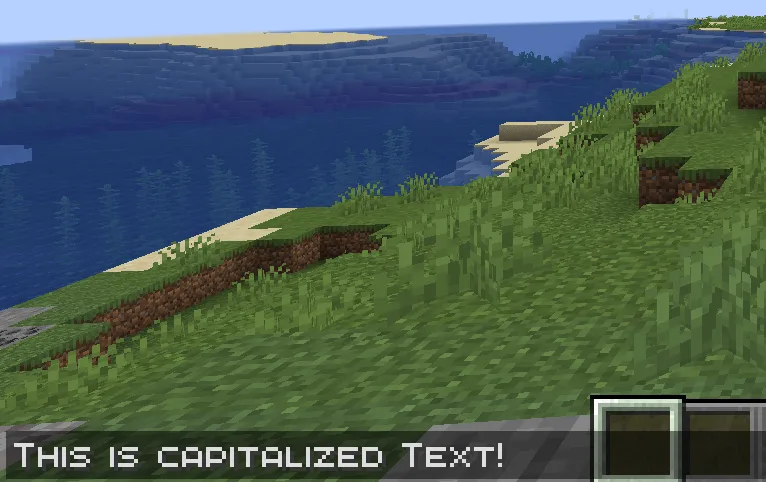
qrafty's Capitalized Font
Этот ресурспак заменяет строчные буквы на уменьшенные версии заглавных, создавая уникальный стиль шрифта, который можно встретить на некоторых серверах.
Ресурспак qrafty's Capitalized Font полностью меняет отображение текста в Minecraft, заменяя все строчные буквы на их заглавные аналоги, уменьшенные на один пиксель. Такой подход создаёт единообразный и стильный вид текста, который часто используется на различных серверах.
Помимо букв, также были отредактированы цифры и некоторые специальные символы, чтобы они лучше соответствовали средней высоте текста. Это обеспечивает гармоничное и сбалансированное отображение всех текстовых элементов в игре.
Ресурспак отличается простотой и эффективностью, не затрагивая другие аспекты игры и сохраняя высокую производительность. Он совместим с указанными версиями Minecraft и создаёт узнаваемую атмосферу благодаря своему уникальному стилю шрифта.